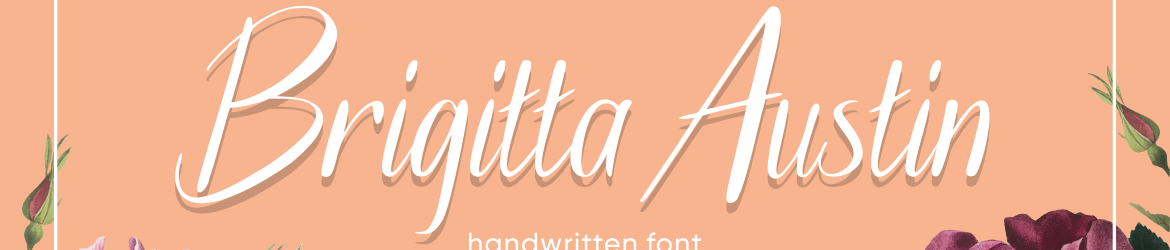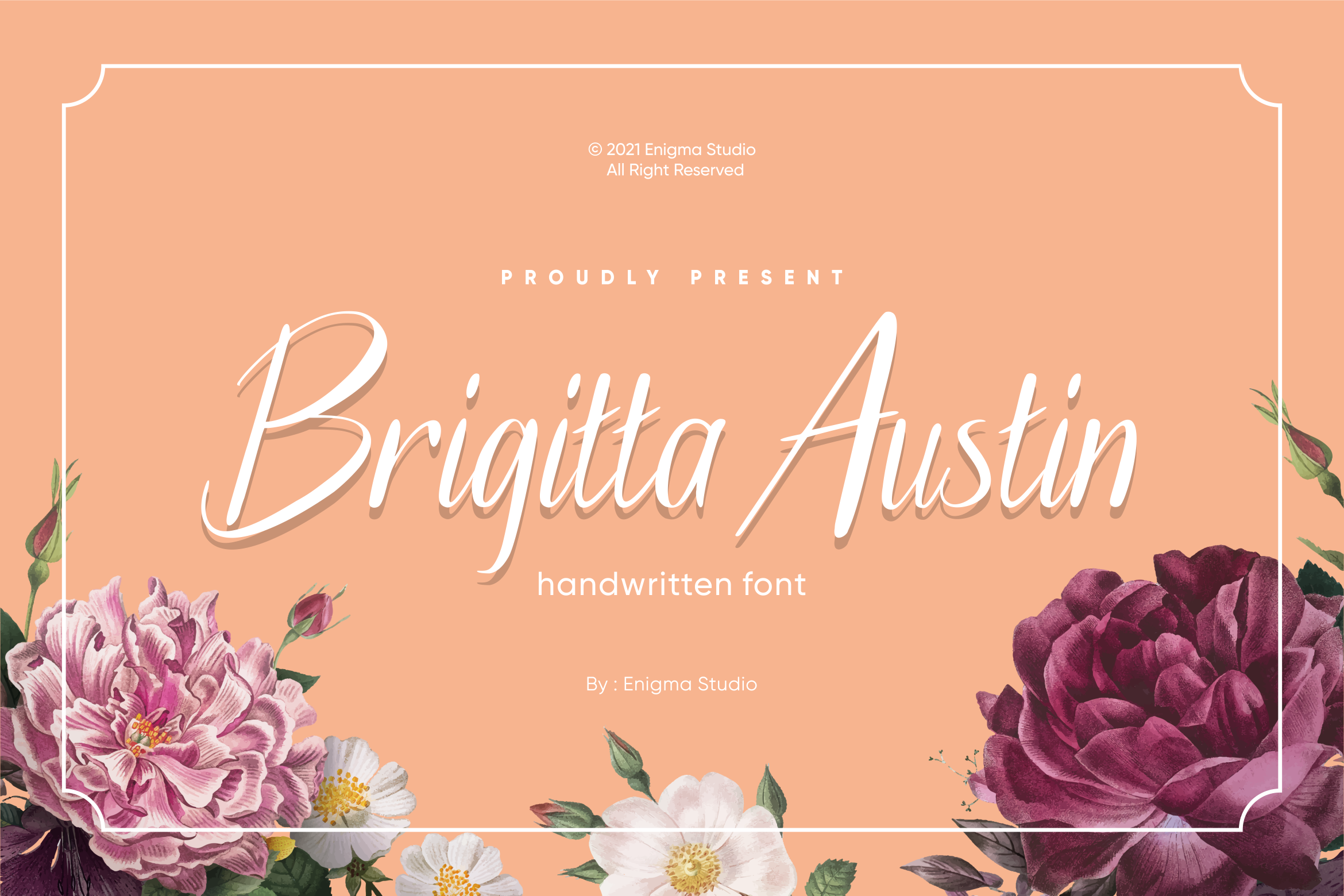
Brigitta Austin Font – Fonte Grátis
Brigitta Austin Font
A Brigitta Austin é uma fonte script escrita à mão perfeita para uma ampla gama de projetos gráficos. Perfeito para embalagens de produtos, criação de marca, revistas e mídias sociais, a Brigitta Austin também é ideal para expressar mensagens acima do fundo em projetos de casamento ou qualquer outra ocasião onde você deseja destacar seu texto com um estilo elegante. Com sua letra fluida e natural, essa fonte se destaca como uma opção versátil que pode personalizar qualquer design com um toque autêntico e criativo. A Brigitta Austin é um recurso visual imperdível para quem busca qualidade em seus materiais gráficos.